Font là gì?
Khái niệm Font
Font chữ hay Phông chữ là khái niệm để chỉ một tập hợp đầy đủ các ký tự (character) và thuộc tính (properties) mà khi sử dụng người dùng có thể tạo ra một văn bản đầy đủ, thống nhất về hình dạng, kích cỡ.
Font chữ bao gồm hệ thống các chữ cái, bộ số, ký tự đặc biệt, dấu câu. Đồng thời Font chữ phải có các đặt trưng riêng và thống nhất để không bị thay đổi (lỗi font) về kiểu dáng, kích cỡ. Hiện nay chúng ta có thể sử dụng hàng triệu font chữ cho các ngôn ngữ khác nhau.
Mỗi một ngôn ngữ khác nhau đều có những đặc trưng riêng về cấu tạo và cách thể hiện. Vì vậy, mỗi ngôn ngữ khác nhau sẽ có font chữ phù hợp khác nhau.
Tiếng Việt của chúng ta cũng vậy, khi soạn thảo văn bản chúng ta cần có font chữ dành riêng. Nhưng không phải cứ có font chữ Việt Hoá là bạn có thể gõ được tiếng Việt.
Font chữ Việt hóa trong Photoshop
Việc sử dụng text (văn bản) trong hình ảnh là không thể thiếu để đa dạng và truyền tải nội dung hình ảnh một cách hiệu quả nhất.
Chính vì vậy, Font rất quan trọng trong việc thiết kế Photoshop. Tuy nhiên, để có thể có được một font chữ đẹp cho Photoshop thì font chữ cần phải hỗ trợ cho loại ngôn ngữ đó.
Nếu font không hỗ trợ cho ngôn ngữ sẽ dẫn dến tình trạng lỗi font. Điều này sẽ khiến người đọc rất khó chịu và không muốn xem bản thiết kế nữa. Đây là lúc bạn cần tìm và tải font chữ sao cho phù hợp và có hỗ trợ ngôn ngữ của bạn.
Vai trò của font chữ khi thiết kế trong Photoshop
Font chữ có vai trò rất quan trọng trong việc thiết kế với Photoshop. Bạn phải vừa lựa chọn sao cho phù hợp với nội dung hình ảnh, vừa phải phù hợp với thị hiếu người xem.
Tất nhiên, bạn vẫn có thể tải font chữ cho Photoshop bằng tiếng Hàn, tiếng Việt hay bất kì ngôn ngữ nào khác nếu bạn thích. Tuy nhiên mỗi Font chữ đều có những đặc điểm riêng cần phải lưu ý.
Font chữ trong Photoshop gồm 3 loại chính đó là Script, Sans và Serif. Theo đó, mỗi Font chữ sẽ phù hợp với những trường hợp khác nhau, cụ thể như sau:
1. Font chữ Script
Script mang phong thái tươi vui, mới mẻ và phù hợp với nhiều hoàn cảnh khác nhau. Cùng với đó, để tạo hiệu quả tốt nhất, bạn có thể thay đổi các sắc độ đậm nhạt của Font.
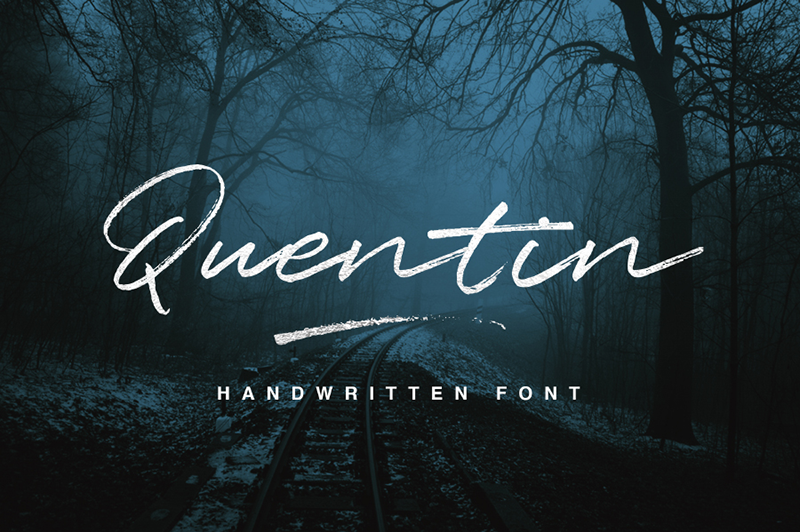
2. Font chữ Sans
Font Sans có độ tròn trịa và mềm mại. Sắc độ đậm nhạt, nghiêng thẳng của Sans cũng đủ giúp bạn biến tấu trong các dự án khác nhau.
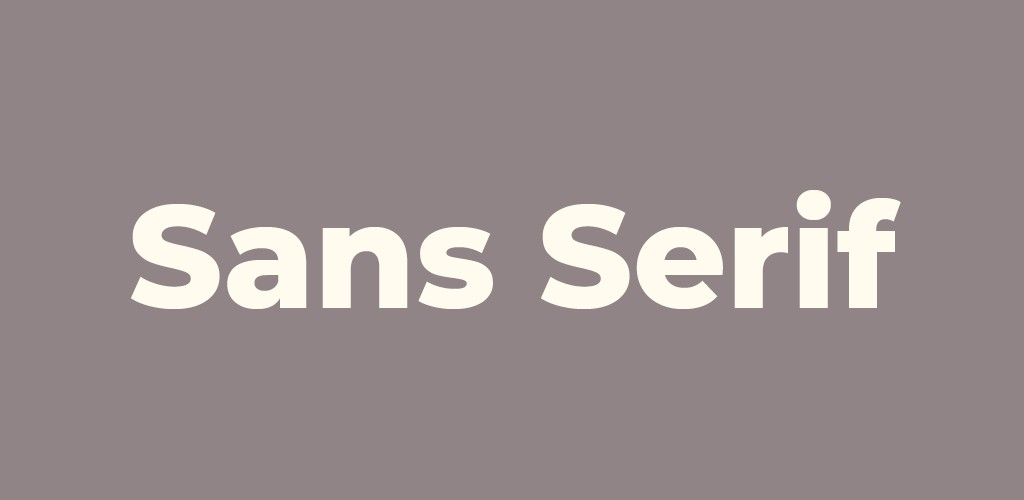
3. Font chữ Serif
Serif có lẽ là loại Font được sử dụng nhiều nhất trong Photoshop nhờ sự thanh lịch, chỉn chu và tạo cảm giác thoải mái khi đọc. Serif cũng được sử dụng nhiều trong các văn bản có tính chất trang trọng.
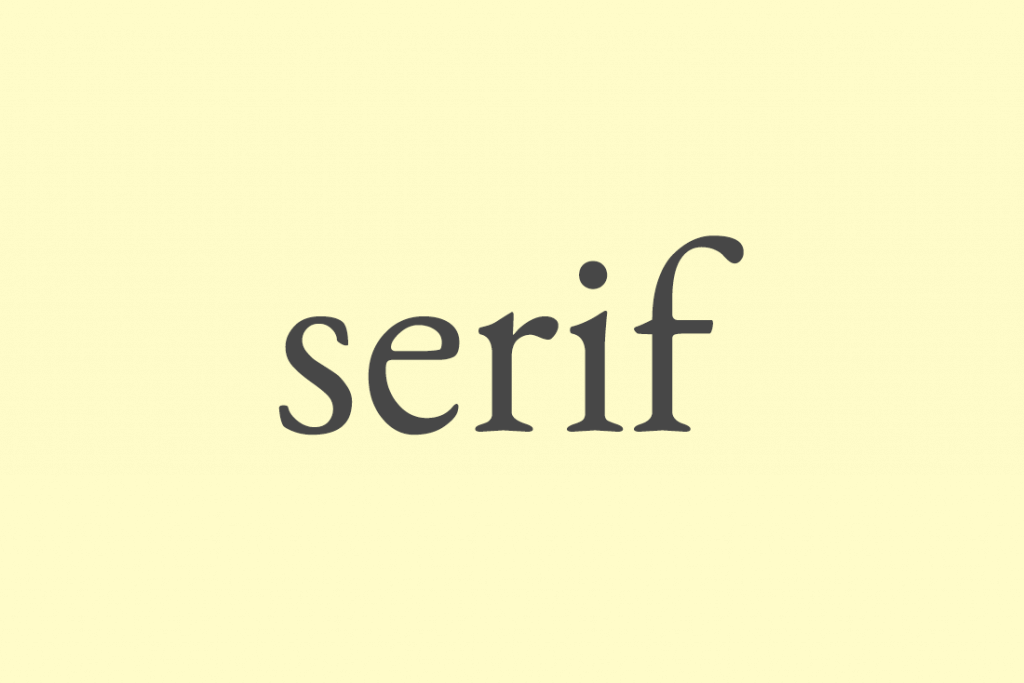
Chính vì mỗi font mang một đặc tính và ý nghĩa riêng, nên khi lựa chọn và tải font chữ Photoshop, bạn cần cân nhắc lựa chọn sao cho nội dung thể hiện đầy đủ nhất. Ngay sau đây, Miko Tech sẽ hướng dẫn bạn cách tải font chữ cho Photoshop.
Hướng dẫn tải font chữ cho Photoshop và cài đặt đơn giản
Để tiến hành cài font chữ cho Photoshop rất đơn giản, bạn cần thực hiện các bước sau đây để tải phông chữ Photoshop CS6 hoặc các phiên bản Photoshop phổ biến khác:
Bước 1: Download font chữ đẹp cho photoshop từ các thư viện trực tuyến
Hiện nay, có cách tải font chữ về Photoshop trên các thư viện phông chữ trực tuyến miễn phí. Bạn có thể thoải mái lựa chọn loại phù hợp với mục đích. Cùng với đó, trên thị trường có rất nhiều nhà cung cấp các font trả phí với những phông chữ đẹp và lạ mắt mà bạn có thể cân nhắc.